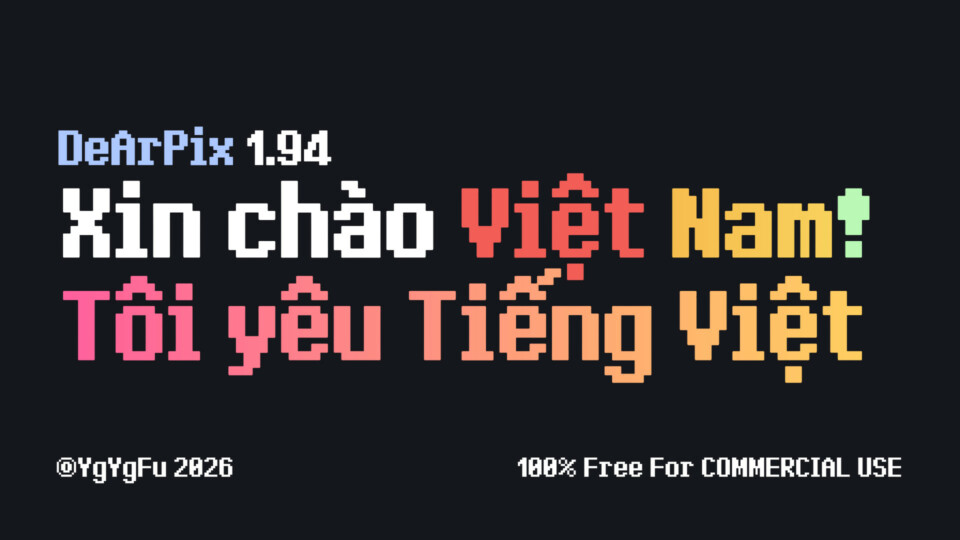
Font Pixel Tiếng Việt DeArPix 1.94
Giới thiệu về Font Pixel Tiếng Việt DeArPix 1.94
Trong thế giới thiết kế đồ họa hiện đại, xu hướng retro và phong cách 8-bit đang quay trở lại mạnh mẽ hơn bao giờ hết. Để đáp ứng nhu cầu sáng tạo nội dung mang hơi thở hoài cổ nhưng vẫn đảm bảo tính bản địa hóa, bộ Font Pixel Tiếng Việt DeArPix 1.94 đã ra đời như một giải pháp hoàn hảo. Đây không chỉ là một phông chữ pixel thông thường mà còn là kết quả của quá trình tinh chỉnh tỉ mỉ để hỗ trợ đầy đủ các ký tự tiếng Việt có dấu. Việc tìm kiếm một Font Miễn Phí chất lượng cao, đặc biệt là dòng pixel art, thường gặp khó khăn do lỗi hiển thị dấu câu. Tuy nhiên, với phiên bản cập nhật 1.94, người dùng có thể hoàn toàn yên tâm về độ sắc nét và tính tương thích trên nhiều nền tảng khác nhau.
Đặc điểm nổi bật của Font Pixel Tiếng Việt DeArPix 1.94
Thiết kế tối ưu cho hiển thị nhỏ
Đặc trưng của Font Pixel Tiếng Việt DeArPix 1.94 chính là cấu trúc dựa trên các ô vuông nhỏ, giúp văn bản giữ được độ rõ nét ngay cả khi hiển thị ở kích thước cực thấp. Điều này cực kỳ quan trọng đối với các nhà phát triển game indie khi muốn xây dựng giao diện người dùng (UI) hoặc lời thoại nhân vật trong không gian màn hình hạn chế. Các nét chữ được sắp xếp khoa học, tránh hiện tượng chồng lấn các dấu thanh, giúp người đọc dễ dàng tiếp nhận thông tin mà không bị mỏi mắt.
Khả năng tương thích và ứng dụng đa dạng
Không chỉ giới hạn trong lập trình trò chơi, bộ font này còn được ứng dụng rộng rãi trong thiết kế áo thun, poster sự kiện công nghệ và các sản phẩm truyền thông kỹ thuật số. Với định dạng linh hoạt, bạn có thể dễ dàng cài đặt font vào các phần mềm đồ họa phổ biến như Photoshop, Illustrator hay các trình soạn thảo mã nguồn. Sự độc đáo của DeArPix giúp sản phẩm của bạn nổi bật giữa hàng ngàn thiết kế sử dụng font sans-serif truyền thống, tạo nên một dấu ấn cá nhân đậm chất “geek” và cá tính.
Lợi ích khi sử dụng Font Pixel Tiếng Việt DeArPix 1.94 trong học tập
Đối với học sinh và giáo viên, việc tiếp cận với các bộ font sáng tạo như Font Pixel Tiếng Việt DeArPix 1.94 mở ra nhiều cơ hội thực hành thú vị. Trong các tiết học tin học hoặc câu lạc bộ sáng tạo, học sinh có thể dùng font này để thiết kế các thiệp chúc mừng điện tử hoặc làm bài thuyết trình về lịch sử ngành công nghiệp máy tính. Văn phong giáo dục và sự trực quan của font chữ pixel giúp các em hiểu rõ hơn về cách thức xây dựng hình ảnh kỹ thuật số từ các đơn vị điểm ảnh cơ bản. Đây là công cụ hỗ trợ giảng dạy trực quan, kích thích tư duy logic và khả năng thẩm mỹ của người học trong thời đại số hóa.
Để tận dụng tối đa vẻ đẹp của Font Pixel Tiếng Việt DeArPix 1.94, người dùng nên lưu ý thiết lập chế độ khử răng cưa (anti-aliasing) về mức “None” hoặc “Sharp” trong các phần mềm đồ họa. Việc này giúp các cạnh của chữ luôn vuông vức, đúng tinh thần pixel art. Ngoài ra, việc lựa chọn bảng màu tương phản cao như trắng trên nền đen hoặc xanh neon trên nền tối sẽ làm nổi bật cấu trúc đặc biệt của bộ font. Quy trình cài đặt rất đơn giản: chỉ cần tải tệp về, giải nén và nhấn chuột phải chọn Install là bạn đã sẵn sàng để sáng tạo nội dung tiếng Việt chuyên nghiệp.
Kết luận về bộ Font Pixel Tiếng Việt DeArPix 1.94
Tóm lại, việc sở hữu một bộ phông chữ vừa mang phong cách cổ điển, vừa hỗ trợ tốt ngôn ngữ mẹ đẻ là điều vô cùng cần thiết cho cộng đồng sáng tạo tại Việt Nam. Font Pixel Tiếng Việt DeArPix 1.94 chính là lựa chọn hàng đầu cho những ai yêu thích sự hoài niệm và mong muốn mang lại trải nghiệm thị giác mới lạ cho khán giả. Đừng bỏ lỡ cơ hội nâng tầm dự án của mình với bộ Font Miễn Phí, Font Việt Hóa, Font Pixel Tiếng Việt DeArPix 1.94 ngay hôm nay để trải nghiệm sự khác biệt trong từng điểm ảnh và độ hoàn thiện tuyệt vời của nó.